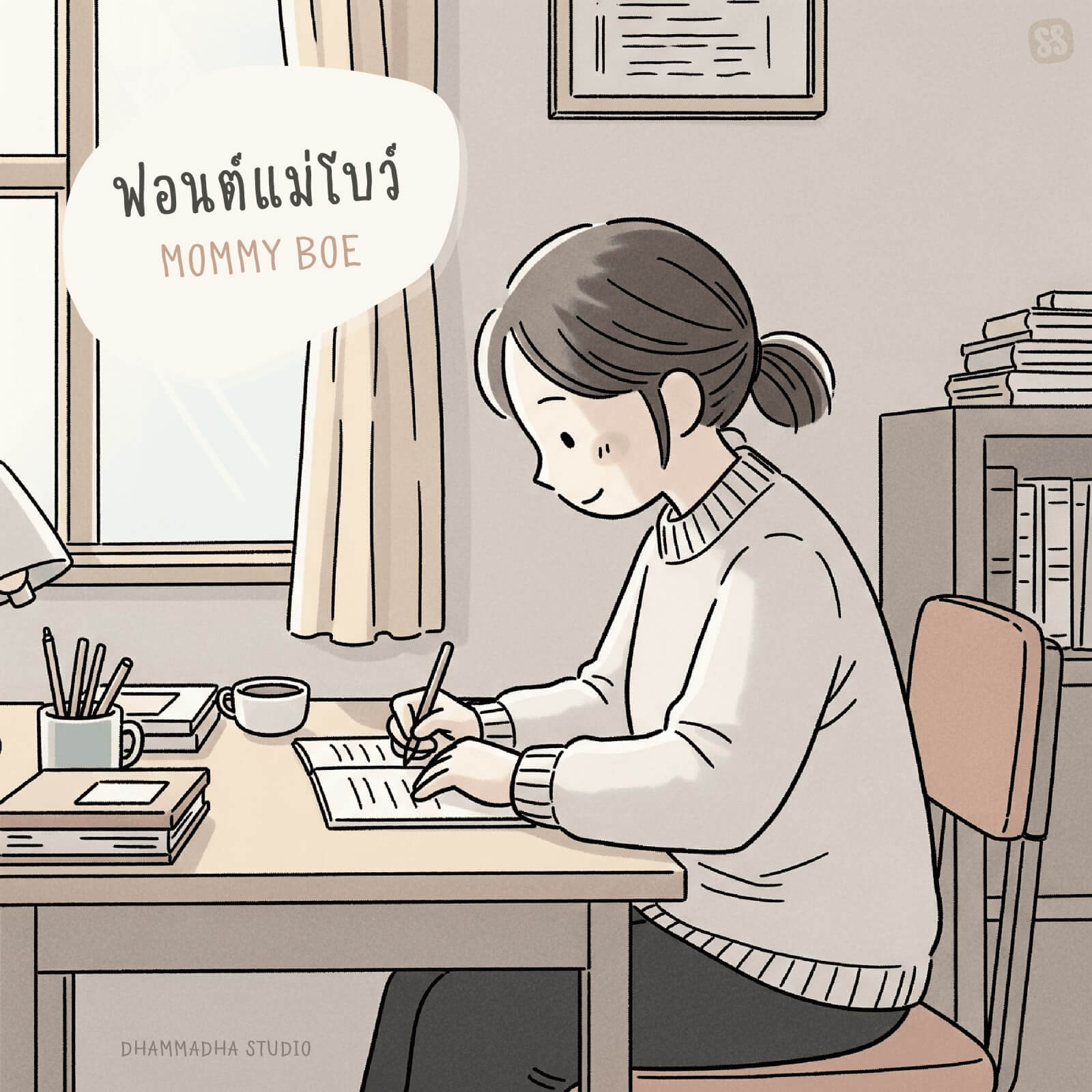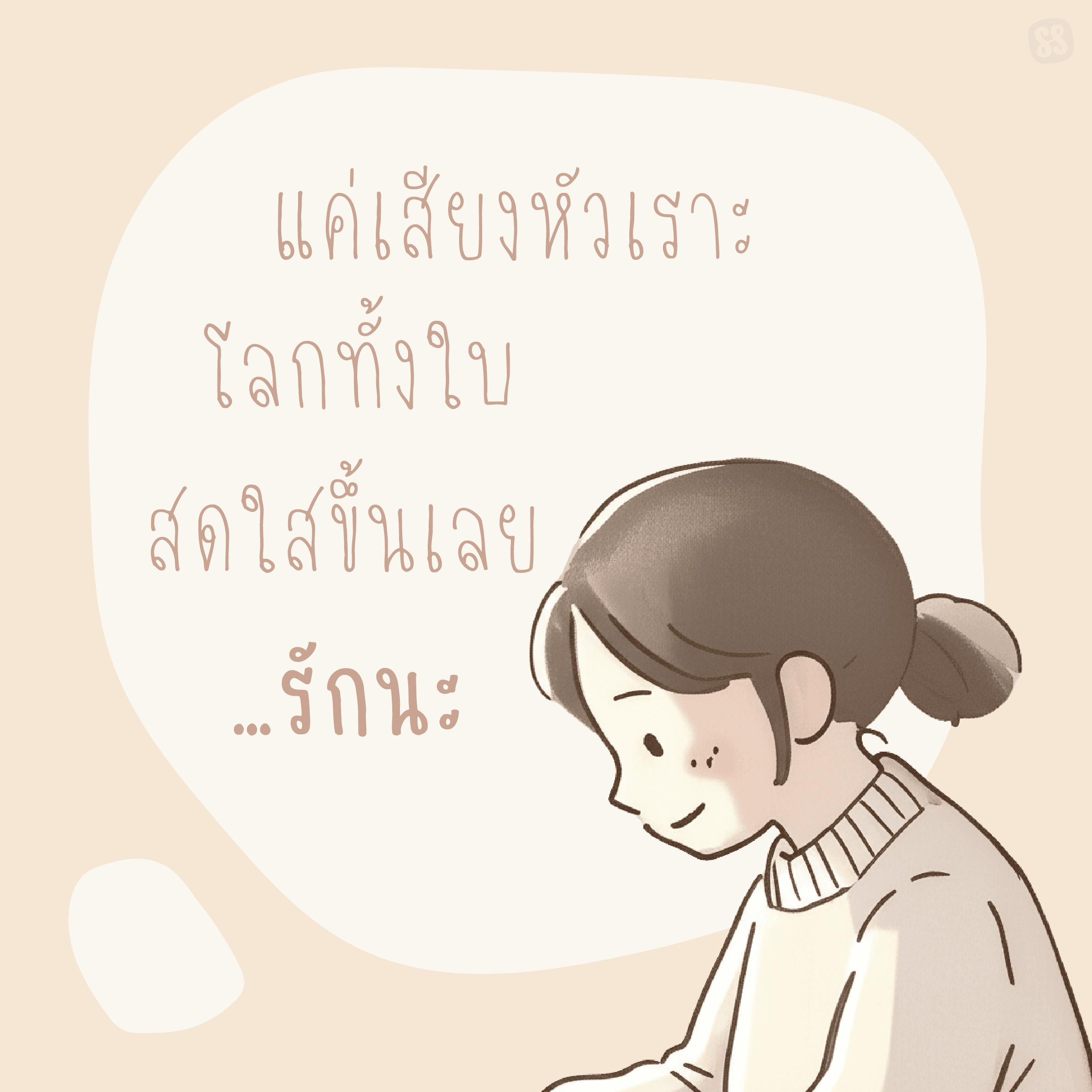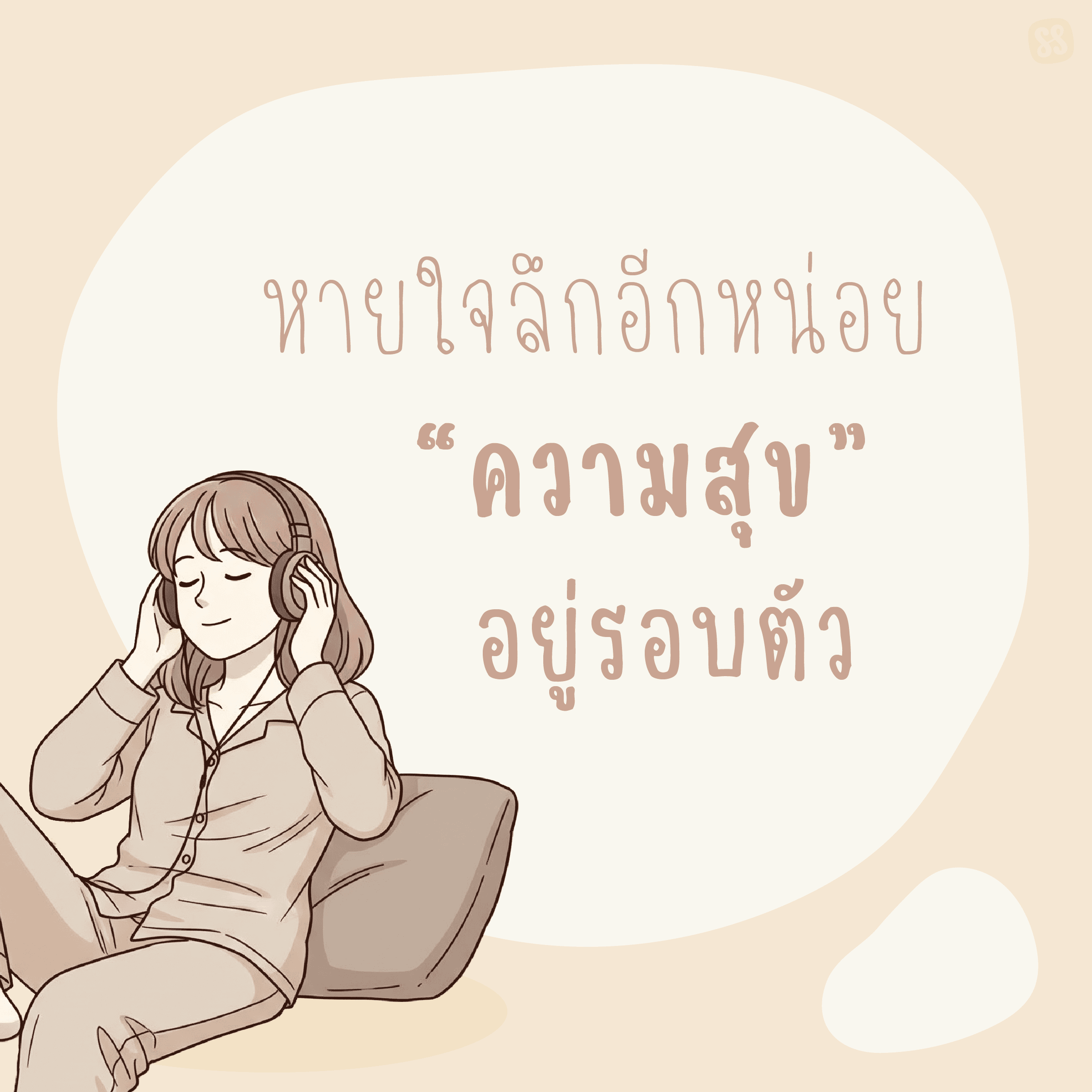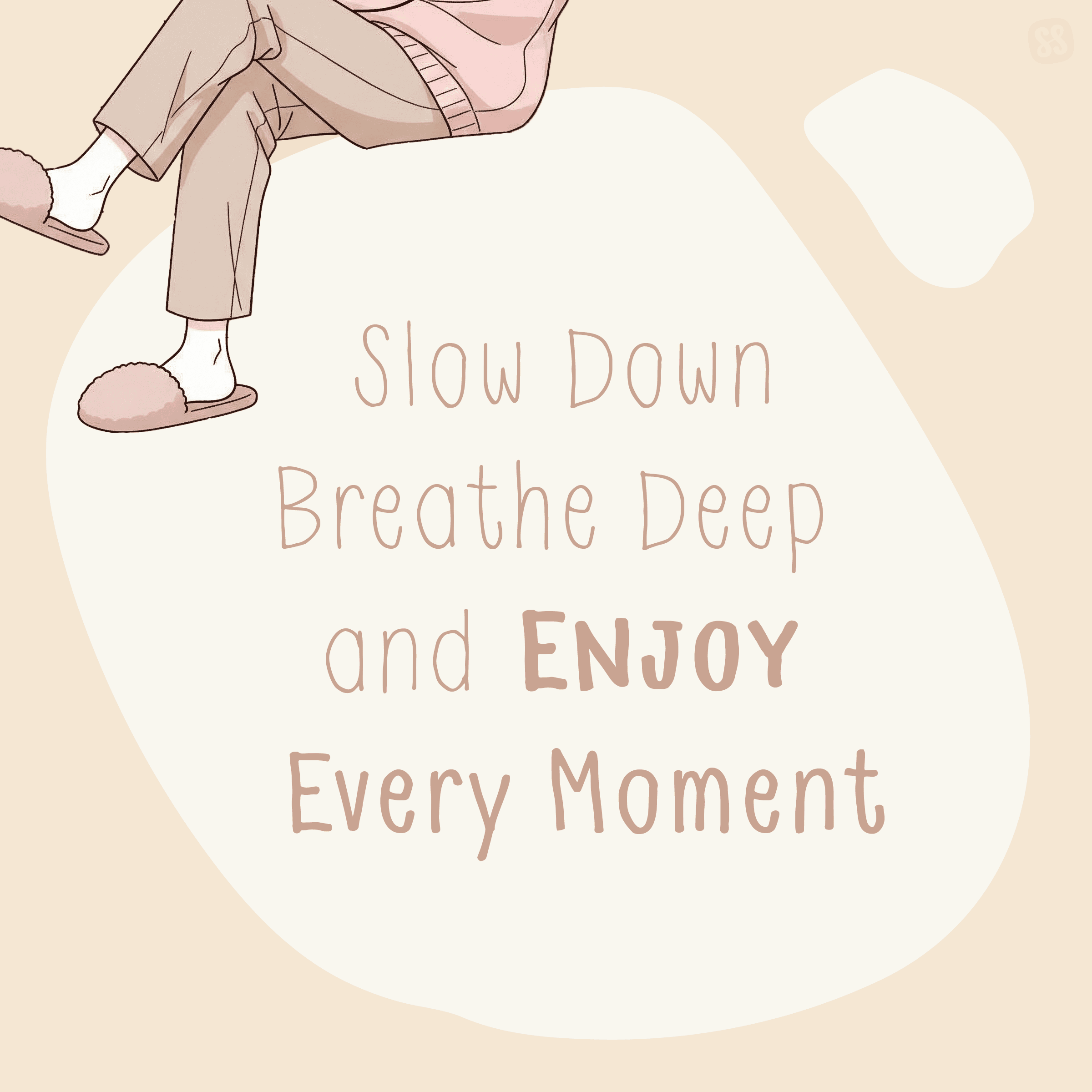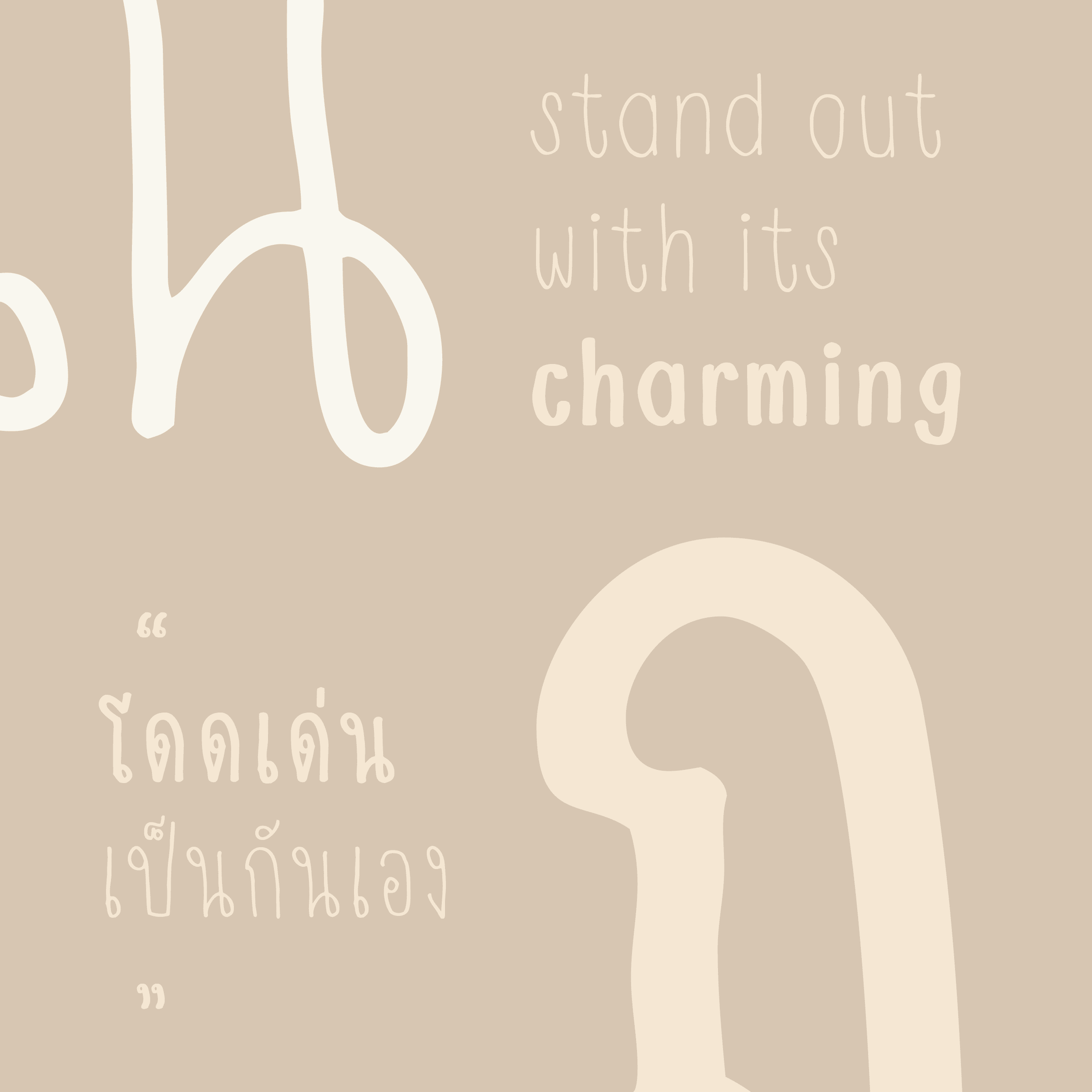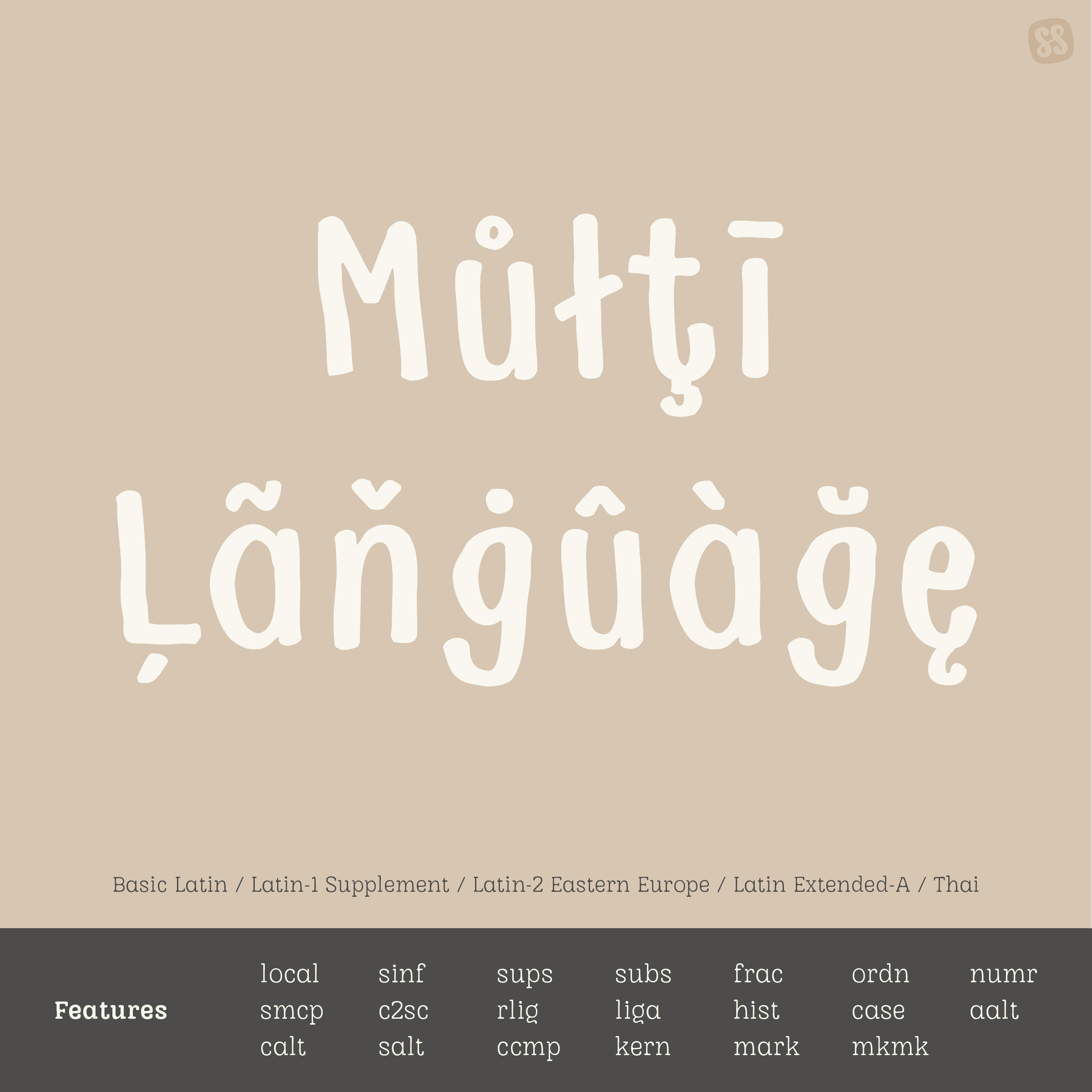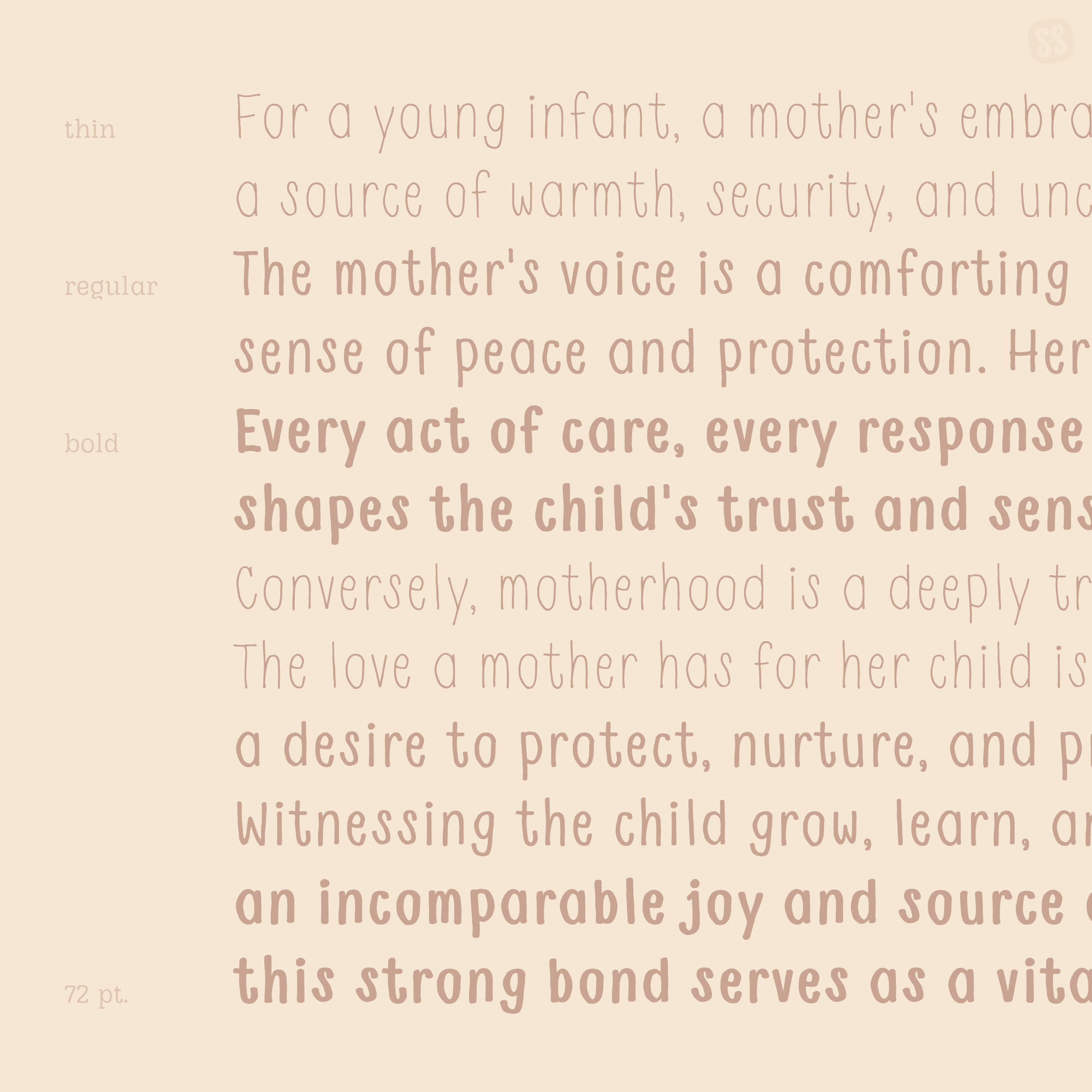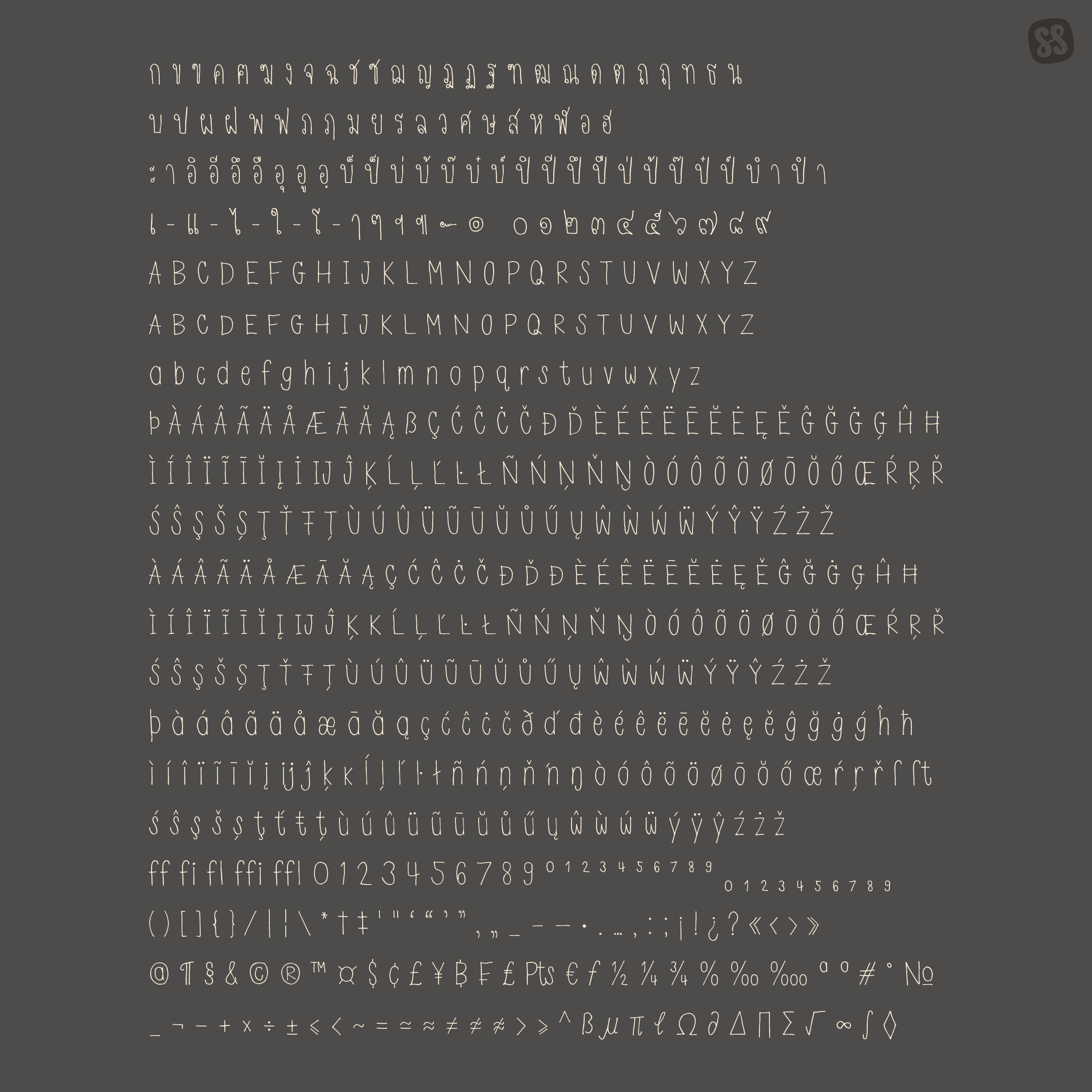
แม่โบว์ | MOMMY BOE
สานต่อความประทับใจจาก ฟอนต์เด็กชายโปเต้ ด้วยลายมือคุณแม่โบว์ ฟอนต์ที่จะส่งต่อความรัก ความอบอุ่น ผ่านทุกตัวอักษร
เพิ่มเติมด้วยการขยายขอบเขตการใช้งานออกไป รองรับการใช้งานได้หลากหลายภาษา ไม่ว่าจะเป็นภาษาไทย ภาษาอังกฤษ รวมทั้งภาษาภาคพื้นยุโรปอีกมากมาย
รองรับการใช้งานได้หลากหลายภาษา ไม่ว่าจะเป็นภาษาไทย ภาษาอังกฤษ รวมทั้งภาษาภาคพื้นยุโรปอีกมากมาย
จัดเต็มด้วย OpenType Features ต่าง ๆ ไม่ว่าจะเป็นการจัดการสระ / วรรณยุกต์ไทย ด้วย Anchor Marking, Ligatures, การทำ Kerning เพื่อความสวยงาม
ชุดฟอนต์ “แม่โบว์” ประกอบด้วยฟอนต์ 3 น้ำหนัก 3 ฟอนต์
MOMMY BOE THIN / REGULAR / BOLD